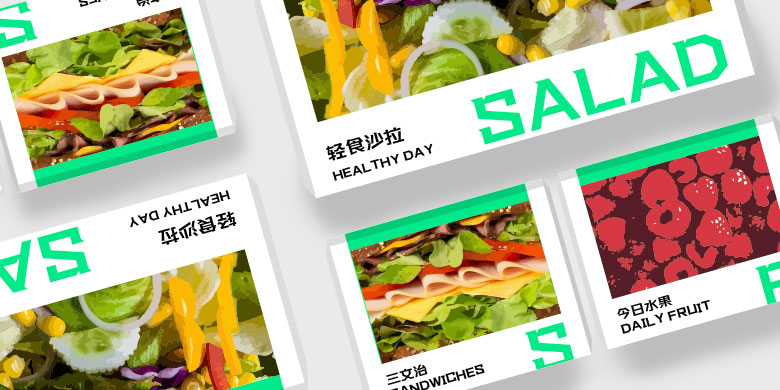
方正坦黑体家族
品牌:方正字库设计师:徐恒震发行时间:2019字库编码:大陆简体(GB2312-80)分类:创意字体字体属性:精品字
坦黑体“坦” 其解释为平而宽广、直率、没有隐讳,这款字体通篇笔画皆为直线组成,表现最纯粹的气质,中宫外扩,字形饱满,并且字型的细节处都有三角形的切角,使得整体的感受力量稳重而不显臃肿。